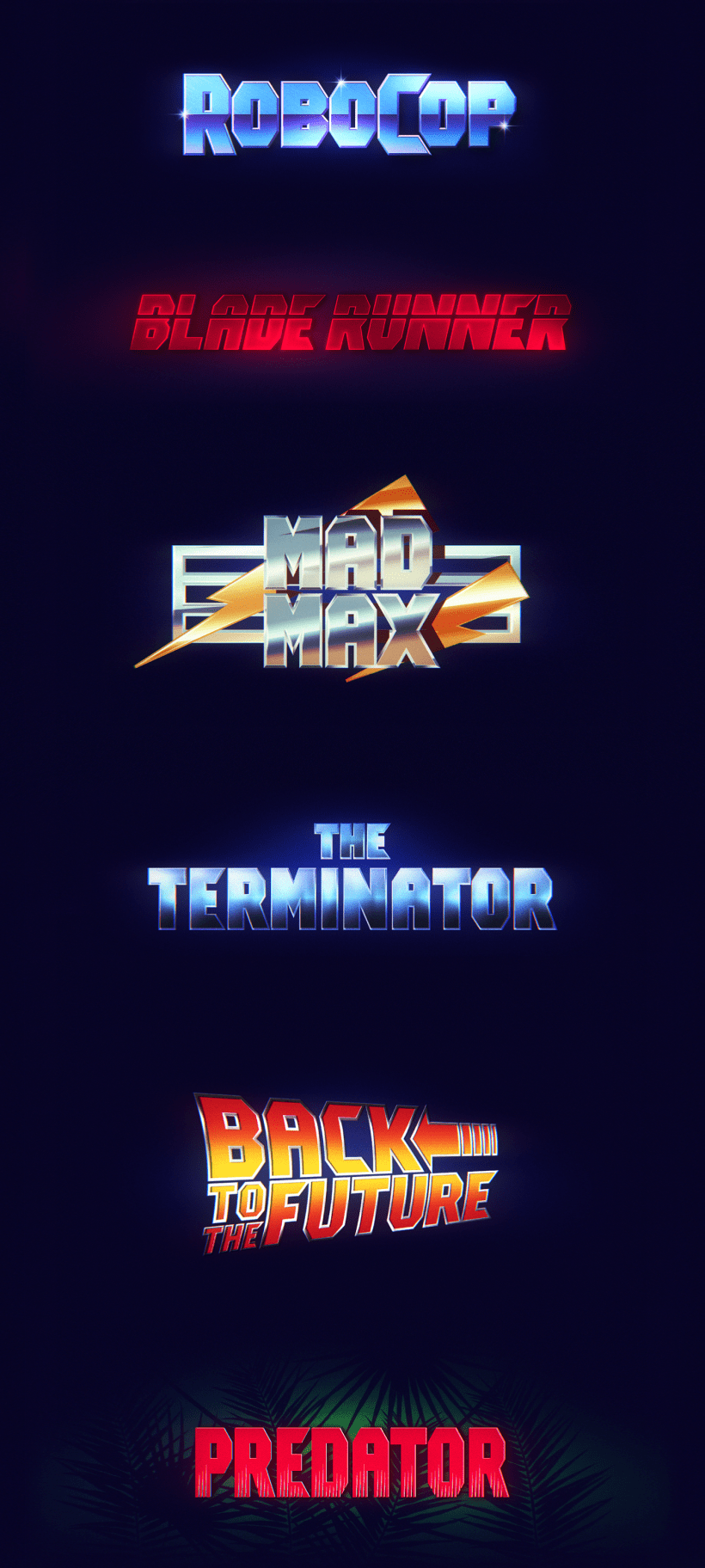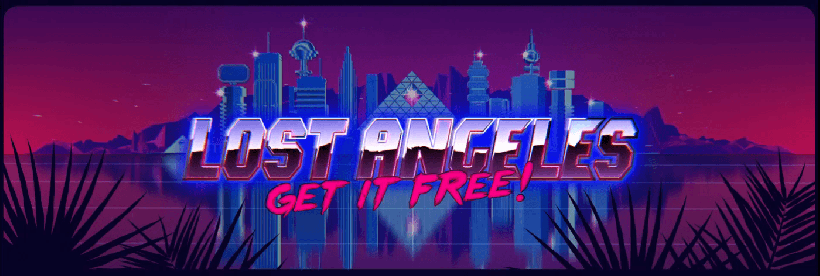
Typographie gratuite : Lost Angeles
Typographie / Police d'écriture gratuite (free font) de style année 80
Les nostalgiques des années 80 vont adorer cette nouvelle typographie gratuite proposée par les talentueux designers russes Mr. Seven, Konfeta et Dmitry Sorokin. Cette Free font pour une utilisation commerciale ou personnelle est à télécharger en bas de l’article.